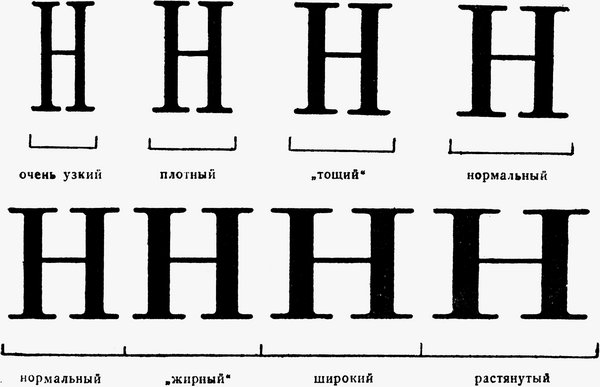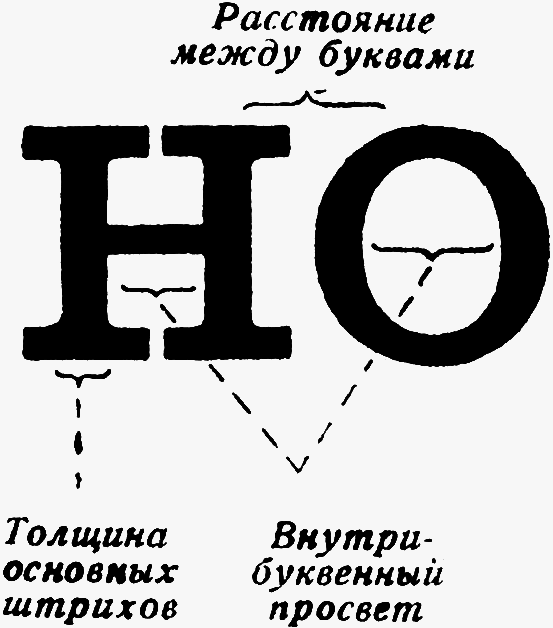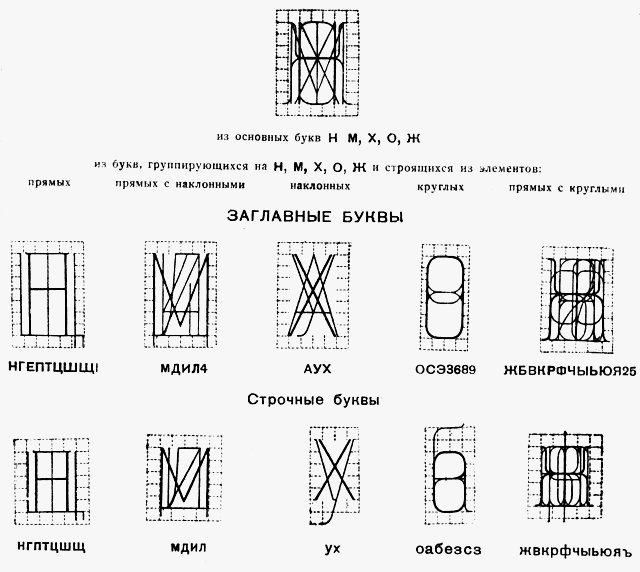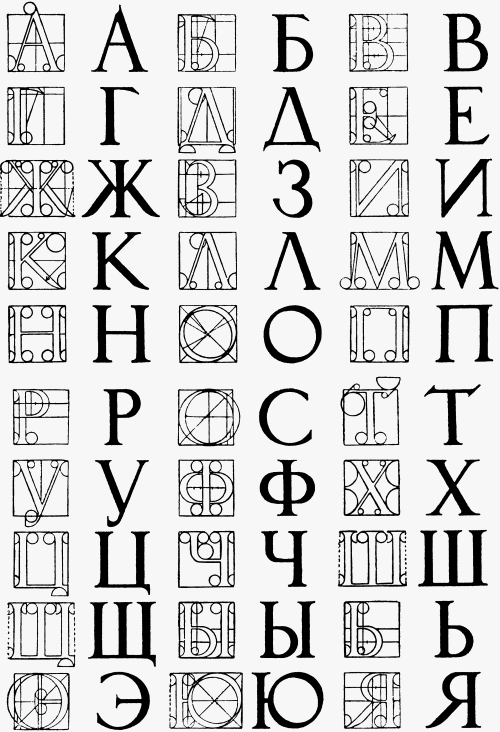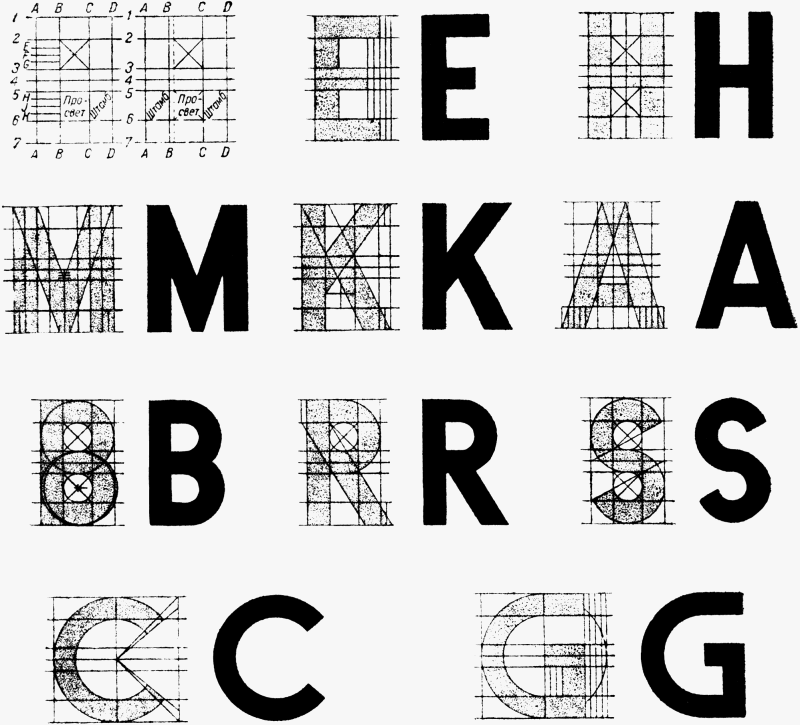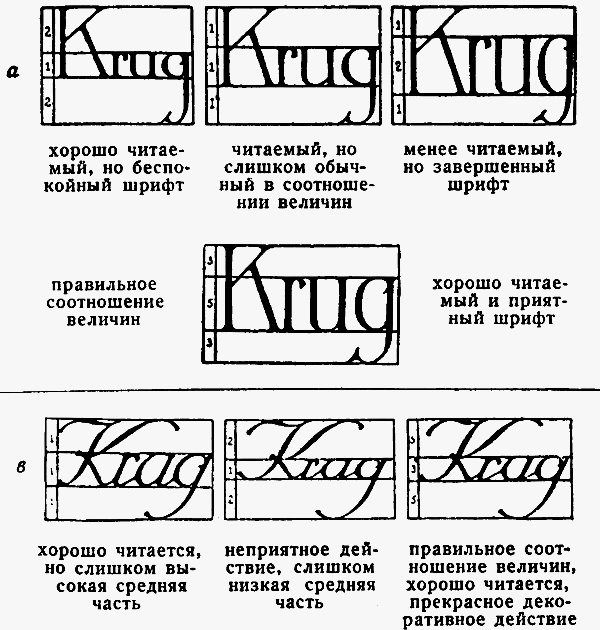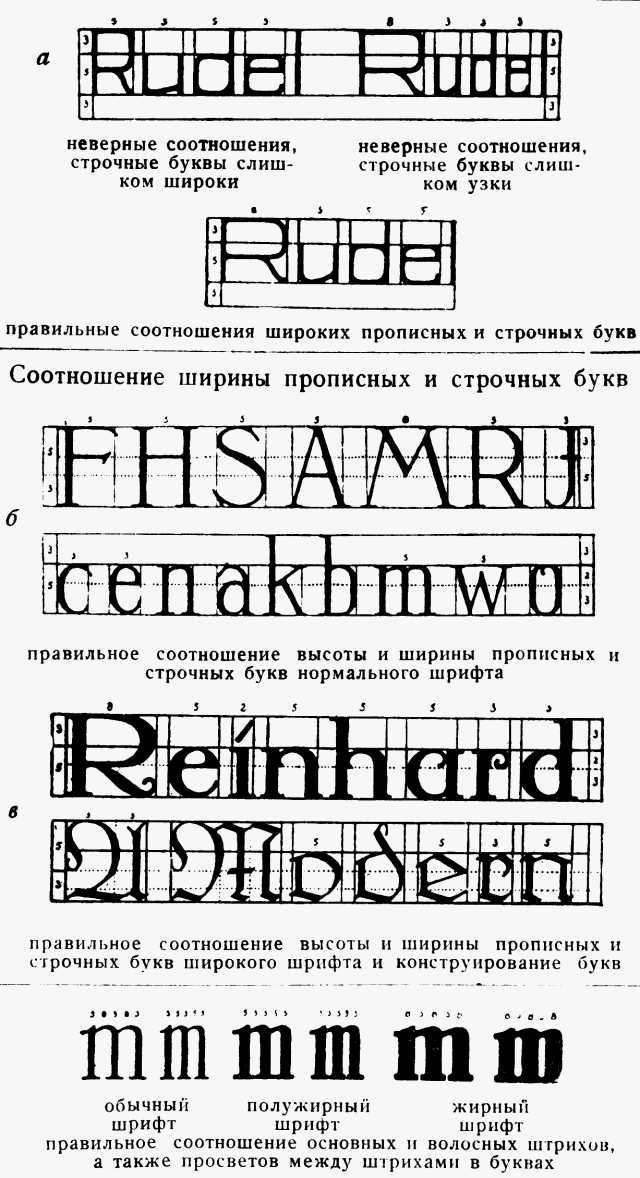
2. Конструкция шрифта. Основные группы шрифтов
При классификации существующих в настоящее время типографских шрифтов их обычно разбивают в основном на следующие пять групп:
Первая группа — медиэвальные шрифты — имеет следующие отличительные признаки: 1) поперечные штрихи (отсечки, или серифы) не образуют с вертикальными штрихами прямого угла, а переходят в них при помощи закруглений (рис. 345, а), размер серифов небольшой; 2) толщина основных и дополнительных штрихов не резко различна; 3) буквы имеют округлую, открытую форму.
Из наших стандартных шрифтов к этой группе относится латинский.
Шрифты второй группы — дидотовские (рис. 345, б) — характеризуются следующими признаками:
Рис. 344 Шрифт "эксельсиор" |
Из стандартных шрифтов ко второй группе принадлежат 6-я гарнитура и альдине.
Шрифты третьей группы — гротески (рис. 345, е) — имеют следующие отличительные черты:
Шрифты четвертой группы — египетские (рис. 345, г) — имеют, как правило, основные штрихи и отсечки одинаковой толщины; отсечки прямоугольны. Разновидностью является итальянский шрифт (рис. 345, д), в котором отсечки толще основных штрихов.
Из пятой группы рукописных шрифтов (рис. 345, е) в стандарте оставлен только один (рукописный "триумф"), кстати сказать, совершенно непригодный для цели, ради которой этот шрифт был включен в стандарт (замена клишированных прописей при наборе букварей).
В заграничной практике применяется целый ряд рукописных шрифтов (см. рис. 331). Кроме того, имеются шрифты, соединяющие в себе черты разных групп, а также ряд декоративных шрифтов.
Рис. 345 Различные группы шрифтов |
Из шрифтов смешанного типа следует отметить медиэвально-дидотовские и медиэвально-египетские. К первым относится, например, применяемый "Правдой" для набора заголовков кэслон. Обладая всеми отличительными чертами медиэвальных шрифтов, кэслон имеет соотношение между основными и дополнительными штрихами примерно такое же, как у обыкновенного шрифта. К медиэвально-египетским относится коринна, где соотношение основных и дополнительных штрихов приближается к египетскому, а отсечки носят медиэвальный характер. 346 347
Из декоративных шрифтов в стандарте оставлен шрифт 1812 г.
На рис. 346 и 347 дана классификация шрифтов по Тибодо.
По классификации Фрезера существует пять главных форм шрифта, а именно: Gothic (готический), Roman (прямой шрифт латинского начертания), Italic (курсив), Block (гротеск) и Script (рукописный). Приводя характерные образы этих основных форм (рис. 348), Фрезер добавляет еще Antique (египетский), считая, впрочем, эту форму разновидностью Roman.
Группа Roman делится на шрифты старого стиля и шрифты нового стиля. Italic (курсив) по существу оказывается тоже своеобразной разновидностью формы Roman.
Легро и Грант делят все шрифты на три главных группы: 1) старого стиля, 2) нового стиля, 3) причудливые, изукрашенные. Интересной особенностью этой классификации является разделение на группы по ширине, в зависимости от длины алфавита, выраженной в круглых. Нормальная длина алфавита (для боргеса) — 13 круглых. Отклонение в ту или иную сторону делает шрифт узким или широким. Принимая нормальную ширину за 100 процентов, получим следующую шкалу (рис. 349):
Эта система была предложена Де Винне и принята в Америке.
В последнее время Научно-исследовательским институтом полиграфической и издательской техники Огиза в проекте стандарта типографских шрифтов предложена классификация, приведенная на рис. 350.
К первому графическому типу относятся шрифты со слабо выраженной (по сравнению со вторым типом) контрастностью между основными и соединительными штрихами; засечки — короткие, близкие по своей форме к треугольнику с закруглением в углах их соединения с основными штрихами; концевые элементы круглых и полукруглых букв (а, с, з и др.) — каплеобразны.
Ко второму графическому типу относятся шрифты с сильно выраженной (по сравнению с первым типом) контрастностью между основными и соединительными штрихами; засечки — длинные, тонкие, либо совершенно прямые ("французский вариант"), либо с легкими закруглениями ("английский вариант") в углах их соединения с основными штрихами; концевые элементы круглых и полукруглых букв — точкообразны.
К третьему графическому типу относятся шрифты с еще более слабо (по сравнению с первым и вторым типами) выраженной контрастностью между основными и соединительными штрихами; засечки — прямоугольные. Срускообразные; концевые элементы круглых и полукруглых букв обрезаны по прямой линии.
К четвертому типу относятся шрифты, в которых как контраст между основными и соединительными штрихами, так и засечки отсутствуют.
К дополнительной группе относятся шрифты, для которых наиболее отличительными особенностями являются либо подражание какой-либо нетипографской технике (рукописные, машинописные и другие имитационные шрифты), либо их резко выраженный орнаментальный характер (различные "оттеночные" шрифты и т. п.). Наряду со шрифтами ясно выраженного графического типа существует ряд шрифтов типа промежуточного, среднего между 1 и 3, 2 и 3 (серии "академическая", "эксцельсиор", "медиэваль", "школьные" и "реклама"). Шрифт "кэслон" (рис. 351) будет являться промежуточным между первым и вторым типами.
Антиква и гротеск
Между оформителями книги давно уже ведется дискуссия о том, какому типу шрифта отдать предпочтение: антикве или гротеску.
Четкость, ясность, отсутствие лишних деталей, строго геометрическое построение формы — таковы достоинства гротеска, по мнению его сторонников.
Рис. 351 Шрифт "кэслон" |
Противники гротеска, наоборот, утверждают, что он "ничего не выражает", "безличен", что он только "бескровный скелет", указывающий на банкротство искусства шрифта.
Попытаемся установить достоинства и недостатки обоих видов шрифта не с точки зрения эстетических симпатий отдельных течений, а с точки зрения научных исследований.
Для большого западноевропейского концерна, который предполагал выпускать собственную газету, было произведено в 1933г. сравнительное исследование двух шрифтов: антиквы (Romanisch) и гротеска (Futura).
Десяти лицам было предложено прочесть 12 строк, набранных тем и другим шрифтом. Был установлен с точностью до долей секунды темп чтения для каждого испытуемого и выведено среднее. Так как шрифт предназначался для газеты, которую обычно читали в вагоне трамвая, метро, то был произведен второй опыт — чтение вибрирующего текста.
И в том, и другом случае оказалось, что гротеск легче читается. При вибрировании буквы гротеска легче узнавались, чем буквы антиквы.
При чтении на расстоянии показатель для антиквы оказался 9,88 и для гротеска — 10,1. При слабом освещении оказалось, что гротеск был видек в то время, когда буквы антиквы еще были расплывчаты. Для гротеска в среднем требовалось освещения на 20% меньше.
Интересные опыты были произведены Научно-исследовательским институтом Огиза в 1931 — 1932 гг. Исследовались три шрифта: латинский (как представитель медиэвальных шрифтов), 6-я гарнитура (один из дидотовских шрифтов) и рубленый, или акциденц-гротеск (группа гротесков).
Результаты советских исследований отличаются от приведенных выше. Основные выводы получены следующие:
- Различие гарнитур сказывается на процессе чтения, и это влияние тем сильнее, чем слабее квалификация читателя.
- При чтении отдельных слов наилучшие результаты дает рубленая гарнитура (на 21 % лучше, чем латинская), далее латинская (на 6% лучше, чем 6-я гарнитура) и на последнем месте 6-я гарнитура.
- По данным не законченных еще экспериментов на читаемость этих трех гарнитур в разных кеглях (от 6 до 16), а также экспериментов со связным текстом, можно считать, что достоинства как рубленой, так и 6-й гарнитуры понижаются с уменьшением кегля и возрастают с его повышением, качество же латинской гарнитуры от понижения кегля не страдает; в связном тексте достоинства рубленой гарнитуры понижаются, тогда как качества 6-й гарнитуры, а особенно латинской, мало изменяются.
- Основное условие читаемости шрифта — это достижение наилучшего выделения фигуры из фона, причем под фигурой следует понимать не только и не столько отдельный графический знак, сколько их группу, образующую графическое слово, являющееся подлинной единицей чтения.
6-я гарнитура, обладая большей диференциальностью отдельных знаков (контраст нажимного и волосного штрихов, резкие длинные волосные серифы), понижает свои качества при группах букв (слияние серифов соседних букв, например и, п, н и др.) и проигрывает в мелких кеглях вследствие истончения волосных штрихов. Рубленая гарнитура выигрывает крупностью очка букв, жирностью равномерных штрихов и простотой рисунка, что в отдельных словах и кратких кусках текста (надписи заголовков, строки обложки или объявления) является решающим преимуществом; к недостатку рубленой гарнитуры следует отнести одинаковость ряда букв: сие, ник, зив, лип, ни и? и небольшие выступы у букв б, р, у, ф и д; эти недостатки создают большую монотонность строки, набранной рубленым, что понижает качество этого шрифта в связном сложном наборе, особенно в мелких кеглях. Латинская гарнитура, не обладая такой диференциальностью отдельных знаков, как 6-я гарнитура (большая равномерность нажимного и волосного штрихов, серифы под углом в виде утолщений основных штрихов), и имея значительно более бледную цветность и меньшее очко по сравнению с рубленым, обладает, однако, рядом достоинств, к которым прежде всего следует отнести достаточную диференциальность графических слов (группы знаков), отсутствие слияния соседних знаков в связном тексте и отсутствие снижения положительных качеств при снижении кегля; эти свойства дают право назвать латинскую гарнитуру универсальной. Не следует забывать, что латинская гарнитура немного превосходит емкостью б-ю гарнитуру, обе же они значительно более емки, чем рубленая, что важно в экономическом отношении".
Рис. 352 Иррадиация |
Американские исследования также подтверждают преимущества антиквы при связном тексте.
При сравнении антиквы и гротеска необходимо остановиться на вопросе об отсечках. Сторонники гротеска отрицали отсечки, считая их ненужными украшениями, нарушающими простоту геометрических форм и мешающими выявлению "функционального" значения буквы.
Между тем значение отсечек в процессе чтения установлено физиологами более или менее бесспорно: отсечки играют при движении глаза по строке роль своеобразных рельсов, облегчая процесс чтения.
Кроме того, отсечки играют определенную роль в связи с явлением иррадиации. Явление это заключается в том, что светлые объекты кажутся большими, чем темные, хотя в действительности они и равны между собой. Это впечатление еще усиливается при соответствующем фоне.
Белый круг на черном фоне (рис. 352) кажется больше, чем черный круг такой же величины на белом фоне.
Явление иррадиации хорошо знали еще архитекторы древней Греции. Угловые колонны, которые с большинства точек зрения выступали на фоне неба (т. е. на фоне очень яркого света), делались немного толще других колонн, видимых на фоне стен здания. Этим достигалось кажущееся зрительное равенство толщины всех колонн.
Вследствие иррадиации круглое о, равное по высоте соседним знакам, например и и п, будет казаться меньше их. Поэтому букву о следует чуть увеличивать против высоты строки (как в шрифте "эксцельсиор").
Вследствие иррадиации края штрихов у букв без отсечек как бы "съедаются" наступающим белым цветом и становятся нечеткими. Отсечки ликвидируют действие иррадиации. Это учитывали мастера XVIII в.: они давали тончайшие отсечки, которые как будто даже и не воспринимались глазом, но способствовали четкости штриха.
Между прочим, серифы могут иметь и отрицательное влияние на удобочитаемость в том случае, если они чрезмерно жирны и перегружают букву.
Гротеск имеет преимущество в том случае, когда есть опасность искажения шрифта, например при офсетной печати и тифдруке. Очевидно, из этих соображений в качестве основного шрифта для фотонаборных машин выбран гротесковый шрифт, так называемый угертипстандарт-гротеск (как известно, фотонабор предназначен главным образом для офсета и тифдрука).
Крупнее: 601x234, 6kb Рис. 353 Схемы отношения основного штриха к дополнительному |
В последнее время лаборатория шрифта Научно-исследовательского института полиграфической и издательской техники, совместно с лабораторией Научно-исследовательского института психологии, под общим руководством. профессора В. А. Артемова разработала метод исследования читаемости шрифта.
Полученные результаты исследования читаемости изолированных буквенных знаков и их сочетаний позволили сделать следующие выводы:
- Для читаемости шрифтов благоприятно сочетание следующих графических особенностей гарнитур:
а) округлый контур,
б) достаточно насыщенный основной штрих,
в) средняя контрастность по насыщенности между основными и вспомогательными штрихами,
г) наличие серифов с достаточными просветами между концами их,
д) пропорции очка и внутреннего просвета, близкие к единице, с преобладанием вертикалей,
е) относительная простота рисунка в целом.- Наиболее широко применяемые в полиграфии для массовых изданий шрифтовые гарнитуры, по данным теоретического графического анализа и экспериментов, располагаются по удобочитаемости в следующем нисходящем порядке:
а) светлые: латинский (27-я гарнитура), акциденц-гротеск (рубленый), обыкновенный (6-я гарнитура);
б) полужирные: латинские, коринна, академический;
в) жирные: гротеск жирный, гермес-гротеск, альдине жирный.- Из шрифтовых гарнитур, наиболее широко применяемых для детской литературы, на первом месте по удобочитаемости стоит латинская светлая гарнитура (27-я). Это относится к литературе для детей с достаточным навыком чтения (3 — 4-й классы начальной школы). Применительно же к детям, начинающим читать, на первом месте по удобочитаемости стоит гарнитура акциденц-гротеск (рубленая).
Крупнее: 600x63, 9kb
Рис. 354 Шрифт с удлиненными штрихами, выходящими за строкуИсследования последнего времени показали, что новый шрифт для детской литературы (типа шрифта "сенчури-скулбук") по удобочитаемости стоит выше и латинской (27-й) гарнитуры, и акциденц-гротеска.
Результаты исследований позволяют сделать следующий педагогический вывод:
а) на первых ступенях обучения шрифтовое оформление имеет огромное значение для читателя; успешность процесса чтения находится в особенно большой зависимости от положительных качеств шрифтовой гарнитуры;
б) на первых ступенях обучения наиболее эффективна та гарнитура, которая отличается сравнительной простотой контура, достаточной насыщенностью штриха, малой контрастностью между штрихами, наиболее четким внутрибуквенным просветом; на дальнейших ступенях обучения лучше воспринимается гарнитура с несколько более сложным контуром и большей контрастностью между штрихами".
Таким образом, распространенная еще недавно точка зрения, что гротеск всегда является наилучшим книжным шрифтом, неправильна.
При выборе в каждом отдельном случае того или иного шрифта не следует забывать, что элементы оформления (интерлиньяж, длина строки, бумага, краски и т. д.) в значительной мере изменяют воздействие шрифта.
В советской печати решающим моментом при выборе шрифта является смысловой, идейный момент. Никто не будет, например, набирать сочинения Дарвина пальмирой или давать в них заголовки шрифтом 1812 г. Специфика издания (вид литературы, читательская группа, способ пользования книгой и т. д.) предопределяет в каждом отдельном случае выбор шрифта.
Характеристика шрифтов
Для характеристики основных изобразительных особенностей шрифта существенны следующие моменты:
Взаимоотношение толщины основных и дополнительных штрихов определяет общее впечатление от шрифта. Если контраст между штрихами велик, то шрифт будет производить впечатление большой цветности; при одинаковых штрихах цвет выявляется меньше, и общее впечатление от шрифта будет несколько монотонное.
Нормы отношения основных штрихов к дополнительным точно не установлены. По Дюреру это отношение определяется, как 3:1.
Приблизительно такое отношение наблюдается в латинском шрифте Рис. 353, а).
По мнению некоторых теоретиков, правильное отношение — 2:1. Близкое к этому отношению имеется в шрифте ?чельтенгем".
В ряде шрифтов (гротески) отношение выражается цифрами 1 :1 (рис. 353, в). В коринне основные штрихи относятся к дополнительным, как 3:2, в 6-й гарнитуре, — как 4:1, в елизаветинском, — как 9:1. (Отношения взяты при корпусе. См. таблицу на стр. 263.)
Пропорции между удлиненными кверху и удлиненными книзу буквами также могут быть различны.
Чаще всего нижние удлинения равняются верхним. В некоторых шрифтах (например пальмира) верхние удлинения больше нижних, в других — нижние удлинения больше верхних.
В одном из немецких шрифтов XIX в. имеется буква g двух разных видов: с обычным удлинением и с очень большим, что дает возможность достигать определенных эффектов в титульных элементах.
Пропорции между буквами неудлиненными и удлиненными различны.
В каролингском минускуле отношение может быть выражено, как 1:2, в первых печатных произведениях Гутенберга, — как 3:4, в швабских шрифтах, — как 5:8. На рис. 354 изображен шрифт первой четверти XX в., где это отношение достигает 1:3. Удлинения в буквах имеют существенное значение в процессе чтения. По мнению Грэсса, крупное внутристрочное очко читается при коротких выступах хуже, чем при длинных. Верхние и нижние удлинения имеют значение не столько для восприятия отдельной буквы, сколько для восприятия целого слова: при чтении мы воспринимаем не отдельные буквы, а слово в целом, и удлинения служат в этом случае опорными пунктами.
Крупнее: 590x476, 18kb Рис. 355 Характерные черты в портретах (худ. И. Шелепянов) |
На рис. 355 приведены два портрета, причем лица даны при помощи нескольких характерных черт. Этого вполне достаточно, чтобы узнать Пушкина и Чехова. Такими же характерными чертами, позволяющими "узнать" буквы, а через них и все слово, являются в шрифте удлинения. Чрезмерное количество удлинений становится моментом отрицательным, что имеет место, например, в армянском алфавите. В русском алфавите незначительное количество букв имеет удлинения книзу и еще меньше кверху. Однако общее количество выступаний за строку в русском алфавите не слишком сильно отходит от нормы, и конфигурация слов в нашем письменном и печатном тексте не монотонна. Но было бы лучше, если бы буквы к и ф также имели удлинения (см. "эксцельсиор", рис. 344).
Подсчеты среднего количества букв в слове и количества букв с удлинениями в разных языках дают следующие результаты (на сто слов текста).
Набор, состоящий целиком из прописных букв, читать было бы утомительно — он слишком монотонен. Такой набор применяется только в титульных элементах или в заголовках, где слов обычно немного.
Крупнее: 641x944, 34kb Рис. 356 Обложка с граматической ошибкой |
Монотонность текста, состоящего из прописных букв, когда глазу не за что "уцепиться", приводит часто к тому, что мы не замечаем ошибок. В обложке, приведенной на рис. 356, не сразу заметна ошибка, допущенная художником.
По данным Старча текст, набранный строчными буквами, читается на 10% быстрее текста, набранного сплошь прописными.
Отношение прописных и строчных букв также может быть различно. В современных шрифтах, как правило, прописные буквы равны по высоте буквам с удлинениями кверху.
Ширина шрифта
Для ширины шрифта решающую роль играет отношение толщины основных штрихов литеры к расстоянию между штрихами. Это расстояние обозначается обычно термином "внутрибуквенный просвет" (рис. 357).
В прежних литературных источниках просвет часто обозначался немецким термином "бунценвайте" или "бунценбрайте".
Крупнее: 553x628, 15kb Рис. 357 Схема внутрибуквенного просвета |
Рис. 358 Отношение основного штриха к просвету |
Различное отношение толщины основного штриха к просвету определяет характер буквы и, следовательно, шрифта в целом.
В светлых шрифтах толщина основных штрихов литеры относится к просвету, как 3:5, т. е. приблизительно по золотому сечению или, округляя, как 3:6. В этом случае просвет в два раза шире основных штрихов. Шрифты с таким отношением имеют достаточно светлый фон и читаются легче других (рис. 358, в). В некоторых светлых шрифтах просвет значительно шире (например, в рубленом или рояль-гротеске). Такой шрифт обычно называют тонким широким.
В жирных шрифтах расстояние между основными штрихами должно быть несколько меньше толщины этих штрихов, иначе шрифт будет расплываться. Наиболее благоприятным отношением в данном случае будет приблизительно 9:11 (рис. 358,г). Однако в некоторых жирных шрифтах просвет равен толщине основных штрихов (рис. 359, а), а иногда и значительно уже их (рис. 359, б).
Крупнее: 507x402, 11kb Рис. 359 Различные оношения основного штриха к просвету |
В узких шрифтах просвет обычно равен толщине основного штриха. Иногда в узких шрифтах просвет имеет такое же отношение к толщине основных штрихов, как и в широких; впечатление узкого шрифта в этом случае создается вытянутыми пропорциями литер (рис. 359,в).
Приводим таблицу, характеризующую отношение основных штрихов к просвету (а также некоторые другие показатели) для ряда шрифтов.
Шрифт как конструктивное целое
Шрифт в процессе чтения воспринимается нами как нечто целое, как единый зрительный образ. Если набрать строку разными шрифтами, то даже неискушенный читатель заметит, что в этом наборе не все благополучно, что единого впечатления не получается. Это показывает, что у читателя уже после восприятия нескольких букв создается общий образ шрифта. На основании этого образа и определяется принадлежность к данному шрифту всех последующих букв.
Можно изменить величину литер от нонпарели до квадрата и выше; можно взять шрифт широким и узким; можно изменить углы литер и получить курсив, — все эти шрифты будут тождественны, так как основная их конструкция не изменилась.
Но достаточно произвести какие-либо изменения в конструкции, например изменить пропорции частей, заменить. круглую форму эллиптической, изменить направление осей, по которым строятся буквы, и характер шрифта сразу изменится.
Рассмотрим, например, "золотой шрифт" Морриса, о котором речь шла выше (см. рис. 326).
Во всех буквах этого шрифта основные штрихи тождественны по толщине, равно как и дополнительные. Литеры А, Н, М, N, О, Q и F вписаны в квадрат; литеры В, Е, L, Z и Т имеют такую же высоту, ширина же их определена по золотому сечению. "Серединный" штрих в литерах А, В, Е, Н, К, Р и S расположен на геометрической середине литеры. Круглые формы в литерах В, Р, R и С определены эллипсом и тождественны одна другой. Литеры Q, О и B; построены при помощи одного и того же круга.
Отношение дополнительных штрихов к основным равно 2:3.
На основании анализа литер мы устанавливаем, что все они в "золотом шрифте" построены не случайно, а закономерно. Эта закономерность может быть выражена определенной конструктивной схемой.
Определенной конструктивной схемой могут быть выражены и все другие шрифты. Они отличаются один от другого различными пропорциями, распределением штрихов в занятом литерой пространстве и геометрическими формами, к которым сведены все элементы литер.
Рис. 360 Определение конструктивной схемы шрифта |
Крупнее: 600x132, 34kb Рис. 361 Конструктивные схемы различных шрифтов |
Для графического изображения конструкций шрифта нужно наложить литеры одна на другую тождественными формами. Это наложение дает характерную для шрифта схему. Накладывая одну на другую литеры, их распределяют по группам, которые дадут 2?3 промежуточных схемы. Так,. для шрифта Морриса мы получим одну схему для вписанных в квадрат литер А, Н, М, О, Т, N и т. д. (рис. 360), а другую схему для литер Р, К, S, R и В. Совмещение промежуточных схем дает общую конструктивную схему, выраженную графически.
При наложении необходимо следить за тем, чтобы тождественные формы были расположены симметрично вокруг центральной вертикальной оси, а штрихи одинаковых направлений совпадали.
Крупнее: 600x316, 30kb Рис. 362 Схема академического шрифта |
Основное в графической схеме шрифта — направление композиционных осей и контур основных форм литер, наложенных одна на другую тождественными частями. Толщина же штриха не определяет конструкции шрифта, который может быть светлым, полужирным или жирным. Поэтому композиционными осями считаются внешние контуры литер.
На рис. 361 представлены конструкции шрифта Морриса (а). Эльзевиров 1635 г. (б), шрифта Академии наук 1748 г. (в), латинской гарнитуры (г) и академического (д).
На рис. 362 показаны отдельные литеры, которые помещены на фоне конструктивной схемы.
Крупнее: 640x572, 37kb Рис. 363 Полиграммы |
В. Н. Адрианов1 при составлении схематической конструкции шрифта делит все буквы алфавита на пять групп по признаку наиболее характерных основных элементов (рис. 363.) Эти группы следующие:
1-я — буквы, состоящие из вертикальных и горизонтальных линий;
2-я — буквы, состоящие из вертикальных и наклонных линий;
3-я — буквы, состоящие из наклонных линий;
4-я — буквы, состоящие из круглых линий;
5-я — буквы, состоящие из вертикальных и горизонтальных линий в сочетании с круглыми элементами.
Наиболее характерными буквами для каждой из этих групп являются буквы Н, М, X, О и Ж из которых может быть составлена общая схема шрифта (полиграмма), четко выражающая его конструкцию (рис. 363). Здесь. же даны полиграммы для каждой группы букв (прописных и строчных). Эти полиграммы позволяют сделать следующие выводы:
Крупнее: 600x320, 15kb Рис. 364 Построение буквы в прямоугольнике |
Оформитель книги сталкивается со шрифтом как с непосредственной работой художника при изготовлении рисованной шрифтовой обложки, заголовка и т. д.
Выполнение шрифта для репродуцирования дает художнику больший простор, чем выполнение шрифта для словолитен. Художник менее ограничен в своих возможностях. Он может дать шрифт значительной изобразительной ценности, но вместе с тем может допустить ряд случайных. непродуманных построений.
|
Рис. 365 Построение буквы в овале |
Основное правило при конструировании буквы (это не относится к "вязи" и орнаментальному шрифту, которые имеют свои законы) — построение ее в квадрате или ином прямоугольнике (рис. 364), в зависимости от пропорций которого изменяется характер буквы. В то же время определенный, заранее установленный характер шрифта будет определять со своей стороны те или иные пропорции прямоугольника, который послужит основой для конструирования шрифта.
Нехорошо, например, в прямоугольнике в (рис. 364) конструировать букву, изображенную в прямоугольнике а: между основными штрихами получится чрезмерно большое пространство, которое исказит обычную для буквы В форму. Таким образом, первое, что должно быть найдено, — это соотношение между прямоугольником и характером буквы. Найденное соотношение определит характер всего шрифта в целом.
Построение буквы на плоской поверхности (страница книги) не в прямоугольной фигуре, а, например, в овале или круге (рис. 365) незакономерно. Буквы такого типа уместны лишь на круглой форме (на вазе, чашке и т. п.).
Второе важное правило построения буквы — целесообразное деление графических элементов буквы на основные и дополнительные.
Крупнее: 600x240, 18kb Рис. 366 Различные отношения основного и дополнительного штрихов |
Могут быть следующие варианты соотношения между основными и дополнительными элементами (рис. 366):
Превращение основных графических элементов в дополнительные (s) не всегда закономерно, так как искажает обычные формы литеры. Столь же незакономерно смешение в одном и том же шрифте различных отношений основных и дополнительных штрихов (г).
Рис. 367 Буква-пятно |
В шрифте, изображенном на рис. 367, некоторые буквы превращены в цветовые пятна; в букве Т все элементы равноценны, в то время как в букве U они различны; буква R представляет собой комбинацию цветового пятна с различными по силе основным и дополнительным штрихами. Такой разнобой в конструкции делает шрифт беспокойным и неуравновешенным. Различная цветовая нагрузка отдельных букв шрифта вызывает еще одно явление: буквы оптически не располагаются на одной плоскости, а кажутся лежащими ближе или дальше в зависимости от цветовой нагрузки.
Рис. 368 Буквы, ледащие в различных оптических плоскостях |
Это явление заметно даже и в том случае, когда разница между цветовой насыщенностью букв и не очень велика. В слове "изобретение" (рис. 368) буквы И как неуравновешенные по цвету с остальными буквами не лежат с ними (зрительно) в одной плоскости.
Крупнее: 600x210, 16kb Рис. 369 Пространственные отношения круга и рамки |
На рис. 369 изображены три случая пространственного отношения белого и черного цвета. В первом случае (а) создается впечатление, что черный круг стоит на каком-то расстоянии от рамы в глубине квадрата; во втором случае (б) кажется обратное — круг выдвигается на первый план, а рама уходит в глубину; в третьем случае (в) круг и рама воспринимаются на одной плоскости.
Взаимоотношение графических пятен, созданное при помощи комбинации различного количества белого и черного цвета, чрезвычайно важный момент в конструировании шрифта. Некоторая рельефность букв, отрыв их от плоскости листа, в процессе чтения является моментом положительным. Этот отрыв создается различным характером внутрибуквенного просвета. Так, буква "О" или "С" кажется выступающей, буква "X" — лежащей в плоскости и буква "I" — уходящей за плоскость.
Крупнее: 600x860, 60kb Рис. 370 Буквы, ледащие в различных оптических плоскостях |
Желание усилить движение по третьему измерению вызвало появление шрифтовых обложек, титулов и т. д., в которых одновременно применяются светлые и жирные шрифты. Часто это логически не оправдано и является чисто формальным приемом (рис. 370). Только у большого мастера это становится органической частью композиции (см. рис. 88).
При оперировании белым и черным цветом надо учитывать явление иррадиации: количество белого цвета в букве может казаться ббльшим, чем оно есть в действительности.
Иррадиация вообще играет большую роль в полиграфии. В отношении иррадиации действие бумаги на шрифт значительно, особенно при тонких шрифтах и при высокой белизне бумаги (например, мелованной). Поэтому достаточная насыщенность шрифта — необходимое условие удобочитаемости. При этом должны быть учтены как цвет, так и степень глазировки бумаги.
Рис. 371 Увеличение круглых букв |
О влиянии иррадиации на края штрихов буквы при отсутствий отсечек мы говорили выше. Мы указывали также, что круглое о вследствие иррадиации кажется ниже прямоугольных букв. Такое же обманчивое впечатление производят и другие круглые буквы (с, е). На рис. 371 видно, что круглые буквы необходима несколько увеличивать, чтобы они оптически казались равными соседним прямоугольным буквам.
Мы видели, что каждый шрифт может быть представлен схемой, определяющей его конструкцию. Единство конструкции — первое и основное требование, предъявляемое ко всякому шрифту. Если часть букв построена по одному принципу, а часть по-другому, то шрифт никогда не будет восприниматься как органическое целое, а без этого немыслимо его художественное качество, и, как показывают исследования, удобочитаемость. Поэтому умение установить конструкцию литеры очень важно.
Прежде всего устанавливаются пропорции прямоугольника, в который вписана буква. Далее следует определить, какую часть стороны прямоугольника занимает основной штрих буквы. Предположим, что ширина этого штриха равна l/7, llw и т- Д- части стороны прямоугольника. Это дает единицу для измерения данной буквы и одновременно всех букв. алфавита. Стороны прямоугольника следует разделить при помощи найденной единицы и соединить деления на противоположных сторонах фигуры, чтобы получилась сетка. Сетка позволит уточнить построение буквы и установить взаимоотношение основных и дополнительных элементов. Эта же сетка даст возможность установить место и направление главных осей буквы.
Рис. 372 Схемы букв Н и О |
Исходными при рисовании алфавита служат буквы Н и О. На основе этих букв можно построить весь шрифт (рис. 372).
Пользование полиграммами облегчает уточнение рисунка каждой буквы, в частности ее ширины и расположения отдельных частей. Уширенные буквы (Ж, М, Ш) обычно имеют полуторную ширину.
При создании художественной шрифтовой формы нельзя, конечно, вначале вычертить квадраты, прямоугольники, оси, а затем уже рисовать шрифт. Эти построения являются не первичным, а последующим моментом и служат главным образом для уточнения творчески созданного шрифта, для его проверки в деталях. Даже идеальная схема, составленная заранее, не обеспечит столь же идеально нарисованного шрифта, создание которого является сложнейшей художественной проблемой.
Выше приводились схемы построения шрифта, данные Пачиоли, Тори, Дюрером, Таглиенте и Жожоном.
На рис. 373 показан русский алфавит, построенный по принципу Дюрера (см. рис. 308) художником Белухой.
На рис. 374 приведены две схемы для построения гротескового шрифта, составленные Милле. Правая схема употребляется для более широкого шрифта. В ней расстояние между штрихами литеры (т. е. просвет) увеличено на 1 часть. При употреблении этой схемы круглые буквы С, G, О, Q и S и цифры 2, 5, 6, 8 и Р остаются такими же, как при левой схеме, т.е. даются более узкими. На этом же рисунке приведен ряд букв, построенных по схеме Милле.
Крупнее: 500x732, 58kb Рис. 373 |
Крупнее: 800x725, 79kb Рис. 374 |
Крупнее: 1200x1400, 194kb Рис. 375 |
Крупнее: 600x630, 32kb Рис. 377 |
Расстояние между вертикальными штрихами буквы при схеме Милле может изменяться в пределах от величины, равной половине толщины штриха, до величины, равной полуторной его толщине.
На рис. 375 даны схемы и расчеты некоторых шрифтов из "Альбома писаных и печатных шрифтов для чертежников и учеников технических школ" М. А. Нетыксы (М. 1906).
На рис. 376 дана схема построения буквы шрифта "Вауег" (1935 г.).
Довольно подробно разработаны правила построения шрифта по канонам золотого сечения. Правила эти следующие (рис. 377 и 378).
На рис. 379 даны образцы шрифтов, построенных по золотому сечению.
Выше мы говорили, что каждый шрифт имеет определенную конструктивную схему, которая может быть выражена графически. Единство схемы является обязательным требованием при рисовании шрифта.
На рис. 380 дана схема построения так называемого "английского" шрифта. Как видно из рисунка, в основу всех букв положен один и тот же овал.
Рис. 376 Схема построения буквы шрифта "Bayer" |
Точность композиционной схемы приобретает особо важное значение при рисовании шрифтов, предназначенных для отливки в металле. Очень. наглядно это показала разработка армянского шрифта для линотипных матриц, выполненная лабораторией шрифта Научно-исследовательского института полиграфической и издательской техники.
Детальное изучение исторически сложившихся форм армянского алфавита дало возможность определить придающие целостность всему алфавиту внутренние принципы графического построения отдельных знаков. Это изучение проводилось по методу указания графических и геометрических соотношений отдельных элементов знака, как строили буквы Леонардо да Винчи, Пачиоли, Дюрер и др.
Так были получены "графемы" — графический каркас буквы, обязательно повторяющийся в любых разновидностях (гарнитурах) шрифта. Анализ построения графем дал возможность обнаружить ряд грубейших искажений, допущенных в шрифтах армянских линотипных матриц немецкими словолитнями.
Из таких искажений можно отметить различие градуса наклона и несовпадение линии шрифта прописных и строчных букв, а также искажение отдельных деталей знаков (что заставляет смешивать некоторые знаки) и даже искажение основы ряда знаков.
Крупнее: 600x851, 89kb Рис. 381 Построения шрифта по схемам графем |
Всех этих ошибок можно избежать, имея графемы шрифта. На рис. 381 дан пример построения по схемам графем армянского шрифта типа гротеск (а) и нового советского шрифта (б).
При конструировании шрифтов нередко механически переносит в русский алфавит принципы построения иностранных алфавитов. Многие художники-шрифтовики, например, часто строят букву И так, как это изображено на рис. 382, т. е. копируют латинскую букву N (см. также рис. 373). Это совершенно неправильно. Как видно на рис. 383, подобное начертание буквы N соответствует исторически сложившейся форме рукописной буквы. В то же время рукописная форма русской буквы И совсем иная. Между прочим, и в иностранных текстах конструктивная схема буквы N, отходящая от схемы римского капитального шрифта, иногда может быть вполне убедительна и уместна (см. рис. 391).
1) Расстояние между буквами
Соблюдение между буквами нужного расстояния очень важно. Часто можно видеть, с одной стороны, слишком тесно поставленные друг к другу буквы, а с другой — огромные, ничем не оправданные интервалы между ними. В слове "КОГДА" (рис. 384) буквы КОГ зрительно воспринимаются, как сдвинутые, в то время как между Г и Д разрыв, подчеркнутый еще сближением букв Д и А.
Такую же неправильность в разбивке мы видим в слове "БЯЛЫНИЦКОГО", где буквы набора поставлены одна возле другой без какого-либо учета их рисунка (рис. 385).
Компонуя из отдельных букв слово, необходимо учитывать оптическую площадь, занимаемую буквой (рис. 386). В соответствии с этим меняется разбивка между буквами. Определяя разбивку, можно исходить из размера просвета. По Милле (см. стр. 270), просвет делится на четыре части. При двух прямых буквах промежуток между ними равняется всем четырем частям, а при других буквах (А, V и т. д.) применяется четверть, половина или три четверти просвета, — как это требуется для создания оптически равных промежутков между буквами. Расстояние между словами должно равняться нормальной ширине буквы.
Крупнее: 640x1178, 91kb Рис. 378 |
Рис. 379 а - шрифт из "Canon Misae" (1458); б - шрифт из молитвенника имп. Максимилиана (1514); в - курсив Альда Мануция; г - антиква Иог. Фробена (1523) |
При некоторых комбинациях букв промежутки между ними могут иметь отрицательную величину, т. е. одна буква может заходить на площадь соседней буквы. Если, например, мы будем иметь комбинацию I (рис. 387), то между буквами будет дан полный интервал. При комбинации II мы дадим половинный интервал. В комбинации III интервал отсутствует вовсе. В комбинациях IV, V и VI интервал отрицательный, т. е. часть правой буквы заходит на площадь, занимаемую левой. При комбинации III можно было дать четверть интервала, а при комбинации IV дать буквы без интервала.
Крупнее: 600x300, 33kb Рис. 380 Схема "английского" шрифта |
При решении вопроса о выравнивании интервалов между буквами необходимо учитывать характерную особенность русского алфавита, придающую ему иной-графический характер, чем у латинского: наличие ряда букв (Д, 3, Л, У, Ч, Э, Я), "открытых" налево. В латинском алфавите таких букв только две: J, Z (рис. 388). Это создает в русском тексте ряд графически трудных буквосочетаний при соседстве буквы, "открытой" направо и "открытой" налево, например ГЛ.
Выравнивание расстояний между буквами приходится производить и в типографских шрифтах (от кг. 16 и выше). Типографские шрифты отливаются, за малыми исключениями, без учета межбуквенных расстояний.
Если в наборе легко можно выравнять промежутки различной разбивкой между отдельными буквами (с помощью шпаций), то в рисованном шрифте придется в случае неудачи переделывать все слово, а иногда. и всю строку.
Поэтому при рисовании шрифта необходима тщательная предварительная разметка интервалов, учитывающая характер смежных букв.
Однако было бы абсолютно неправильно, компонуя шрифтовую строку, начать работу с цифрового расчета интервалов. Необходимо прежде всего построить ее наглаз, решить так, как это подсказывается непосредственным чутьем художника. И только затем уже математически уточнять размеры интервалов (половина, четверть и т. д.). Может оказаться, что в отдельных случаях придется дать не полный интервал, а три четверти интервала, или не четверть, а треть интервала. Разметку рекомендуется делать не сразу на оригинале, а предварительно на другом листе бумаги.
2) О ширине букв
Буквы типографского шрифта, как мы знаем, по ширине не равны между собой. В одних случаях эта разница естественная, вызываемая самым характером начертания буквы (например, ниш). В других случаях она будет искусственной, как, например, между буквами Е и F или между буквами 5 и G в шрифте Дюрера (см. рис. 308).
Желание некоторых теоретиков объяснить эту разницу "невежественностью" Дюрера слишком наивно. Бесспорно, великий художник сделал эти буквы разными по ширине намеренно, чтобы нарушить монотонность шрифта, придать ему больше графической выразительности.
Рис. 382 Заимствованная конструкция буквы "И" |
В шрифтовых работах современных художников (обложки, титульные листы, заголовки и т. д.) также часто встречаются буквы различной ширины. Иногда это делается случайно, иногда сознательно, правда, не всегда достаточно убедительно.
В примере б (рис. 389) круглые буквы даны гораздо шире остальных. Зрительно это неоправдано (слово как бы делится на части), но может быть до некоторой степени объяснено желанием художника противопоставить круглые буквы прямым. В случае а нет ни зрительной, ни логической убедительности. В примере в неодинаковая ширина букв закономерна. Более узкая буква ч препятствует разрыву между буквами ы и а, который произошел бы в результате уширения ч. Уменьшение ширины отдельных букв в целях ликвидации оптических разрывов имеет место в некоторых типографских шрифтах (рис. 390).
Рис. 383 Рукописное и печатное начертание буквы "N" и "И" |
Рис. 384 Оптический разрыв между отдельными буквами |
Следовательно, различная ширина одинаковых по характеру букв в работе художника допустима. Необходимо только, чтобы это было сделано умело и убедительно.
На рис. 391, а буквы Е и L равны по ширине остальным буквам. На рис. б эти буквы даны более узкими. В отношении буквы L это убедительно, так как уменьшается белое пятно между L и I. Букву Е следовало бы сделать несколько шире. В деталях эта буква также выполнена плохо (средний штрих).
Буква О в первом случае взята такой же высоты, как остальные, и кажется меньше их. Во втором случае эта буква несколько увеличена и зрительно кажется одинаковой по высоте с остальными буквами.
3) Рукописные шрифты
Во многих шрифтовых художественных работах как в нашей, так и в иностранной практике применяется шрифт, подражающий рукописному, свободно нарисованному. Выполнение подобных шрифтов, производящих впечатление сделанных очень свободно и легко, требует от художника большого умения и твердости руки, которые только и могут обеспечить необходимую простоту и гармоничность (рис. 392).
Рис. 385 Оптический разрыв между отдельными буквами |
Рис. 386 Оптическое поле, образуемое буквами |
Допустимы ли вообще рукописные шрифты при оформлении? Не противоречат ли они общему характеру печатной книги?
Элементы обложки и переплета могут существенно отличаться по своему характеру от других элементов книги. Обложка, выполненная рукописным шрифтом, может быть вполне уместной, если она применена в соответствующем роде литературы, например, в художественной. Гораздо больше возражений, чем рукописная, должна вызвать обложка, набранная, например, академическим шрифтом при наборе книги рубленым шрифтом, так как в данном случае мы будем иметь сочетание одинаковых по характеру построения, но разных по стилю шрифтов.
Рис. 387 Схема интервалов |
Рукописный шрифт и обычный типографский различны по конструкции. Поэтому не всегда бывает удачным смешение рукописного шрифта с наборным, в особенности, если наборный резко отличается по рисунку от рукописного (рис. 393). Как было сказано выше, рукописные шрифты (типографские) широко применяются в настоящее время оформителями книги США в титульных элементах.
Применение рукописного шрифта в тексте книги (например, в заголовках) требует большей осторожности, так как здесь он стоит в непосредственной близости к печатному шрифту.
Рис. 390 Буквы разной ширины в наборном шрифте |